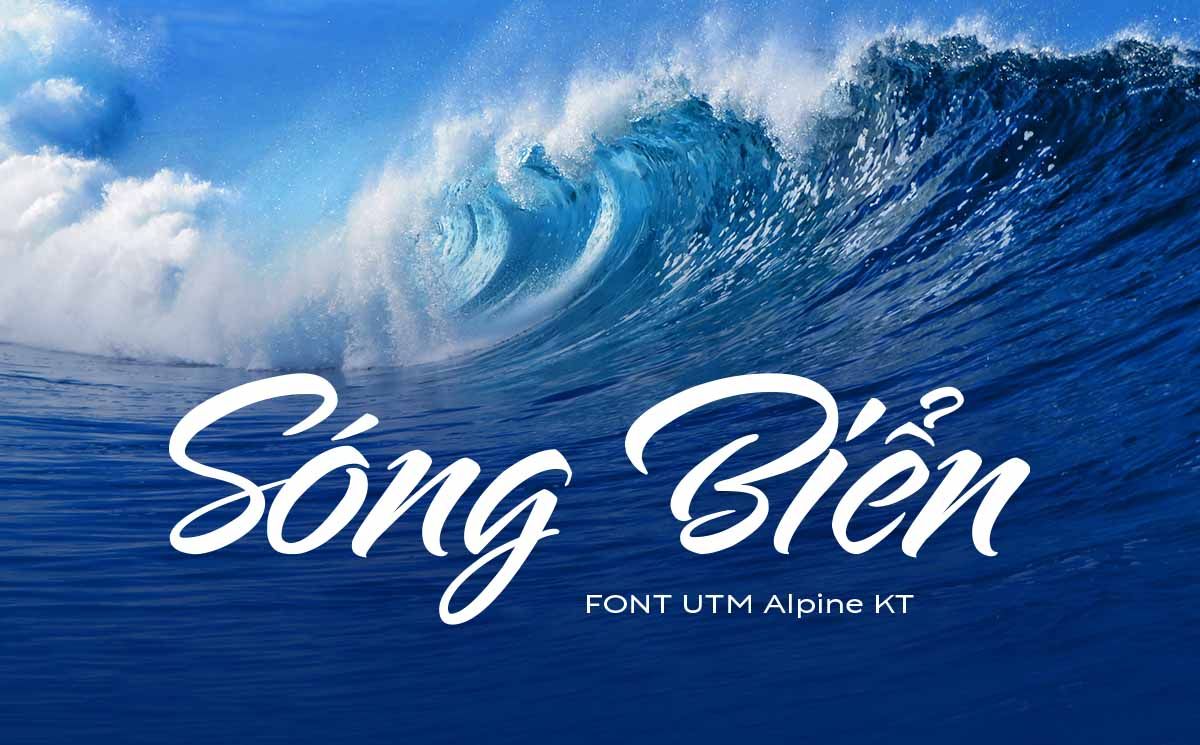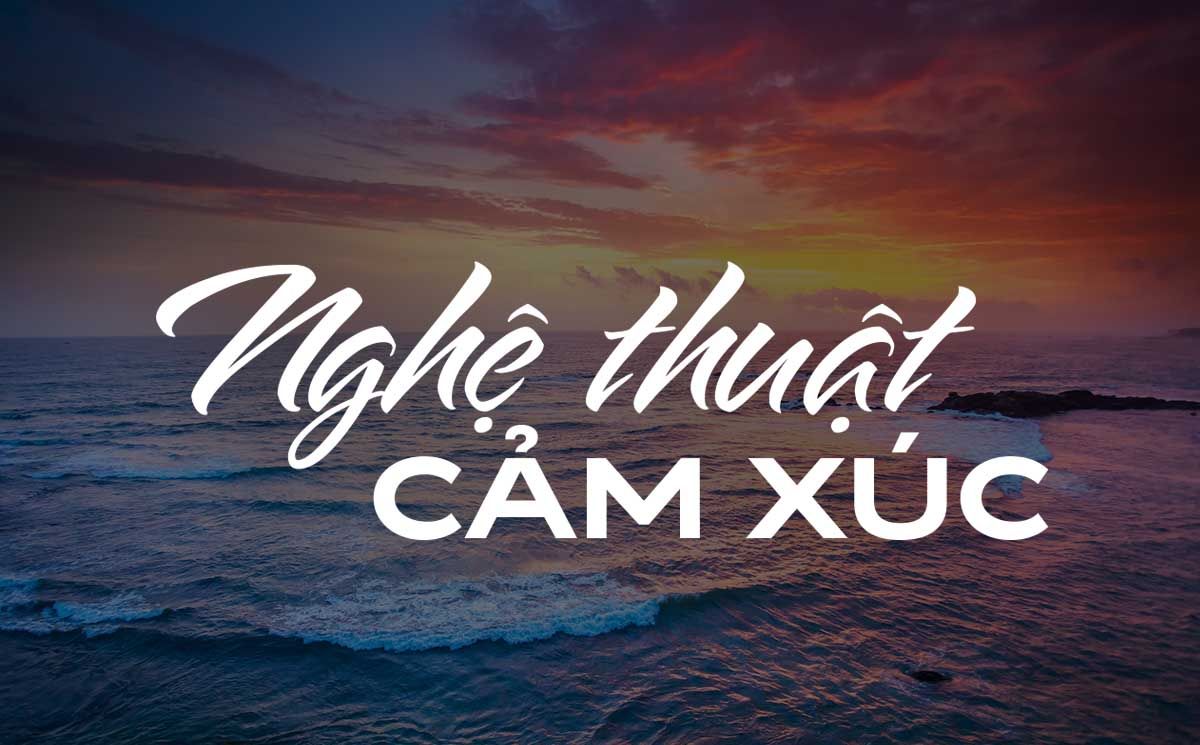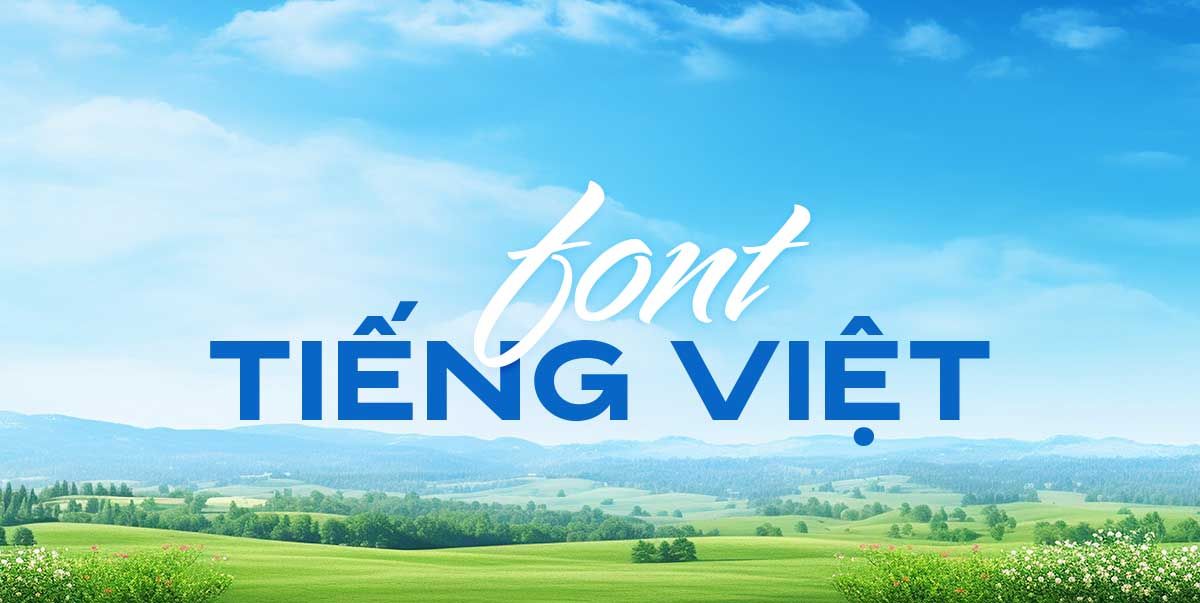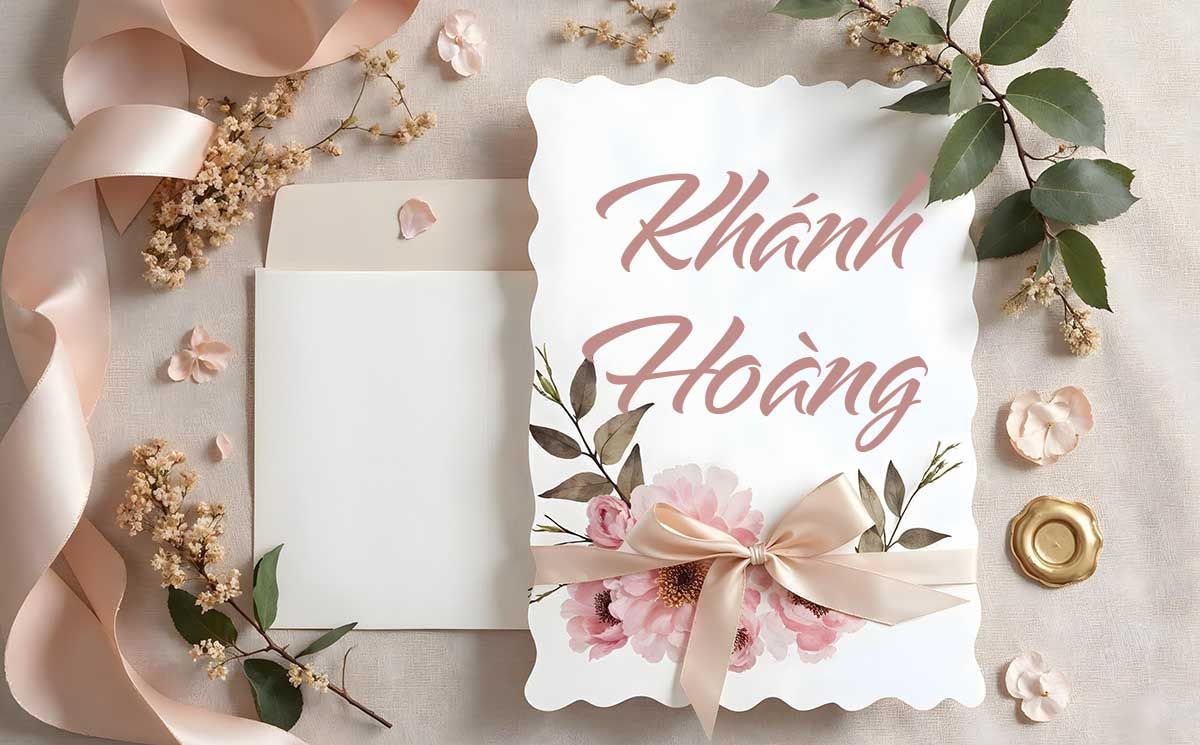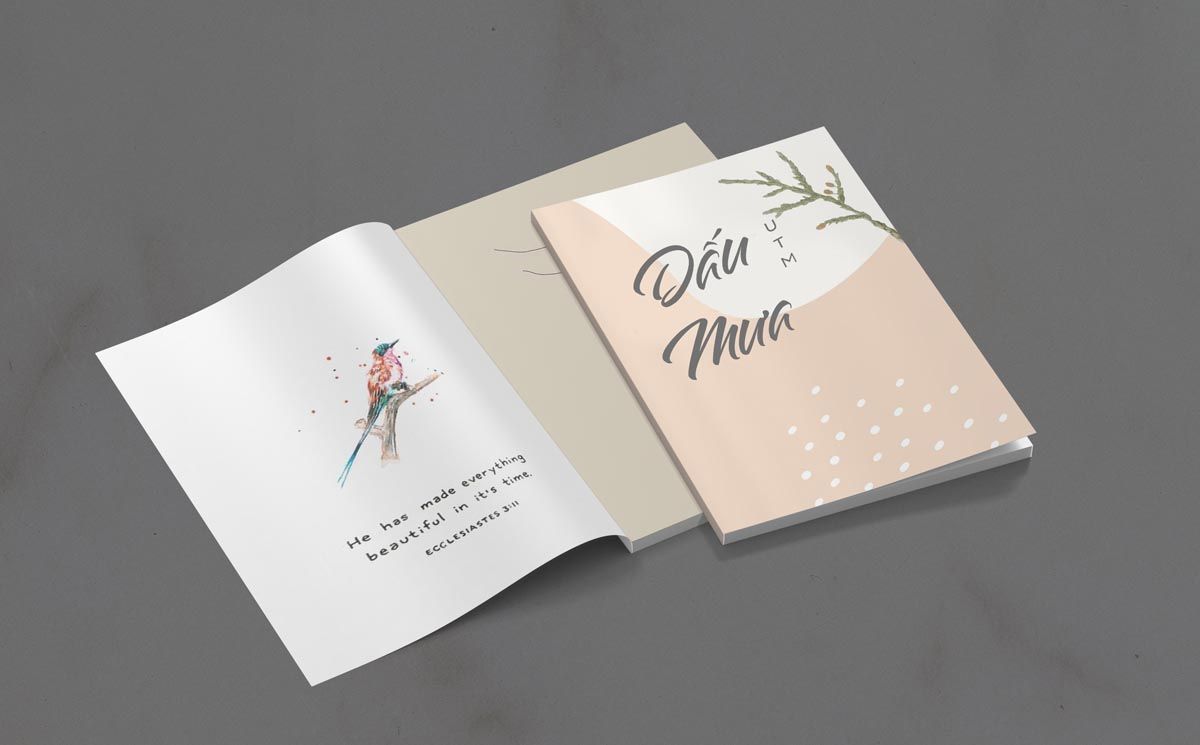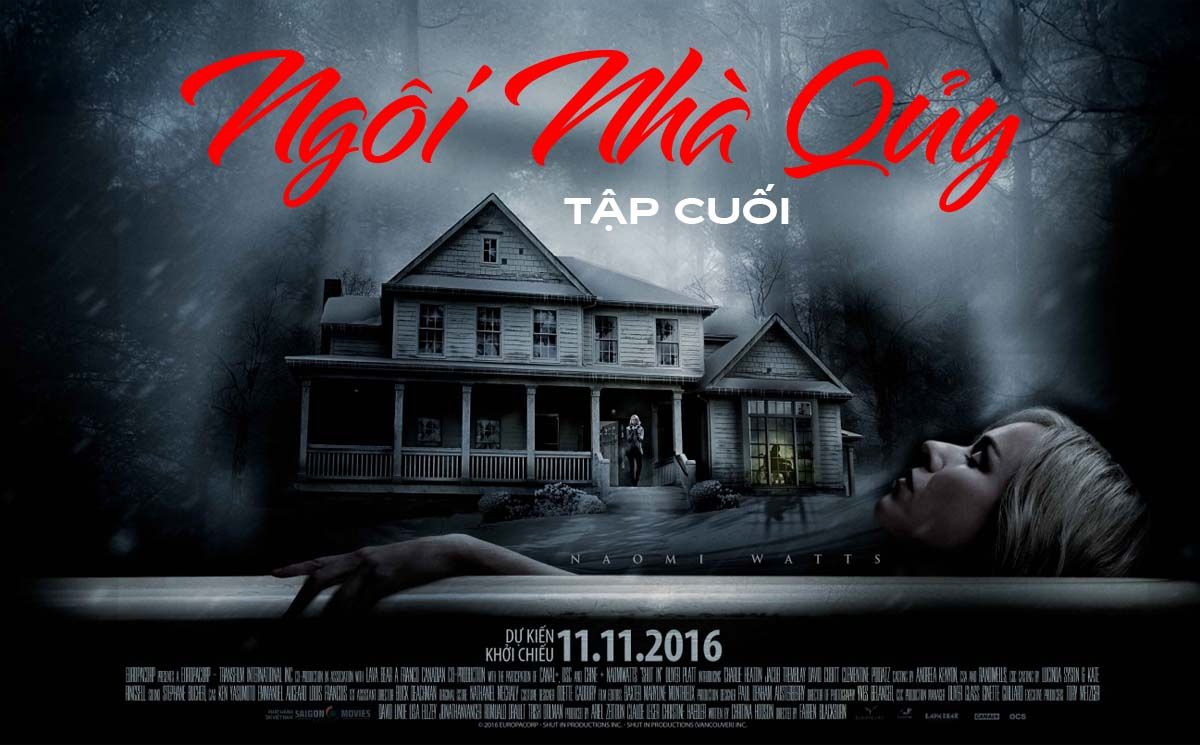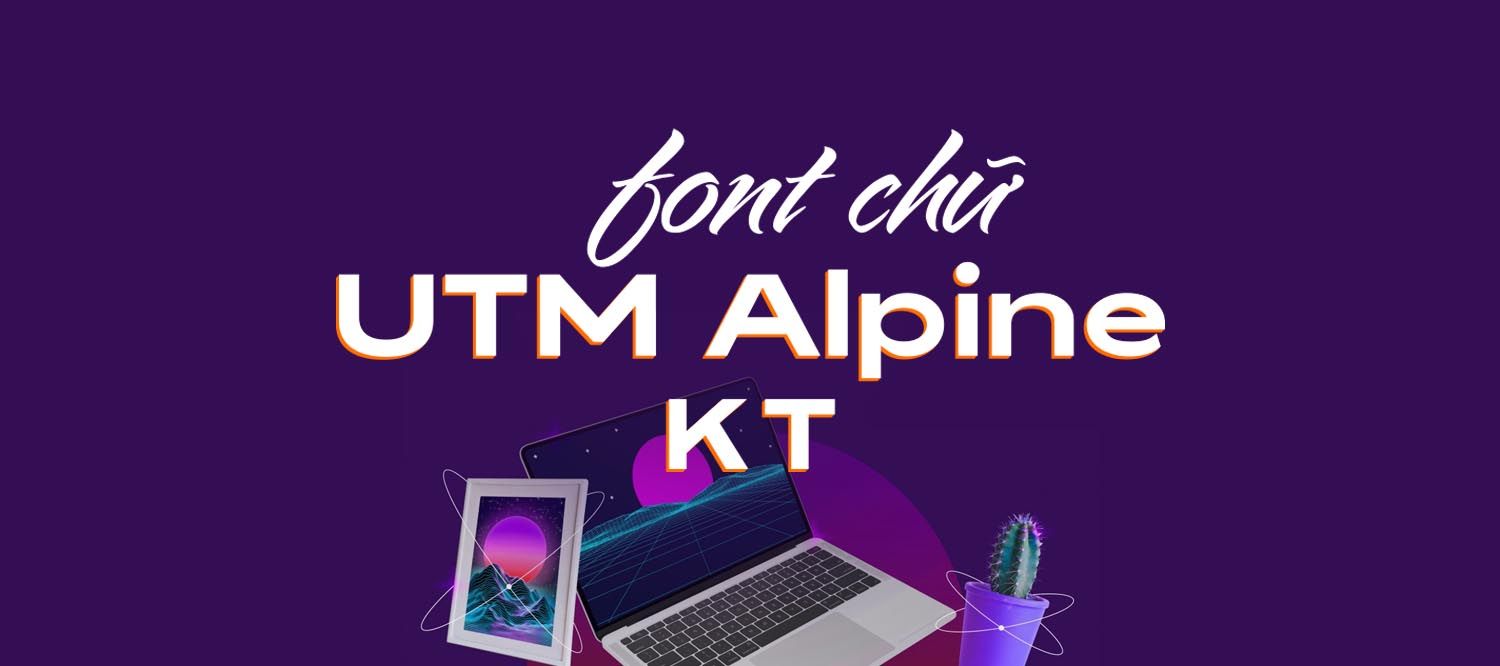
Bạn đang tìm kiếm một font chữ viết tay Việt hóa mang phong cách nghệ thuật, thanh lịch và đầy ngẫu hứng? Font UTM Alpine KT chính là lựa chọn tuyệt vời dành cho các nhà thiết kế đang cần điểm nhấn sáng tạo cho thiết kế tiêu đề, typography hay thiệp mời.
UTM Alpine KT là một font chữ viết tay được Việt hóa bởi nhóm Urban Type Management (UTM) – nổi tiếng với nhiều bộ font đẹp, hỗ trợ đầy đủ tiếng Việt. Phong cách của font mang hơi hướng tự do, phóng khoáng như những nét bút viết tay đầy nghệ thuật.
Font sử dụng các đường nét mảnh, sắc sảo, kết hợp các nét gãy và lượn mềm mại, tạo nên hiệu ứng thị giác đầy ấn tượng. Đặc biệt, các ký tự thường được nối liền, mô phỏng chuyển động mượt mà của bút lông hoặc bút máy.
Font UTM Alpine KT tái hiện lại vẻ đẹp mềm mại của chữ viết tay thủ công, nhưng được cách điệu hiện đại và đầy cá tính. Các nét chữ thanh mảnh, có độ nghiêng nhẹ, giúp tạo nên dòng chảy uyển chuyển, sinh động như đang viết bằng bút máy cao cấp. Những nét đầu – cuối thường được kéo dài một cách tinh tế, mang lại cảm giác tự nhiên, đầy cảm xúc cho từng con chữ.
Một trong những ưu điểm lớn nhất của font UTM Alpine KT chính là khả năng hiển thị tiếng Việt hoàn chỉnh, bao gồm đầy đủ dấu thanh, chữ hoa – chữ thường và các ký tự đặc biệt. Nhờ đó, người dùng hoàn toàn yên tâm khi sử dụng cho các thiết kế mang tính bản địa như: thiệp mời, typography tiếng Việt, tiêu đề báo chí, bìa sách,...
Dù được xếp vào nhóm font chữ viết tay nghệ thuật, UTM Alpine KT vẫn giữ được sự cân bằng giữa thẩm mỹ và tính ứng dụng. Bạn có thể dùng font này cho các dự án cần sự trang nhã, tinh tế (như thiệp mời, thư cảm ơn), hoặc phối hợp với font sans-serif hiện đại để tạo nên các bố cục tương phản sáng tạo trong thiết kế poster, tiêu đề, bao bì...
Với nét chữ mềm mại và thanh lịch, UTM Alpine KT là lựa chọn lý tưởng cho các mẫu thiệp cần sự trang trọng nhưng vẫn gần gũi. Font đặc biệt phù hợp cho thiệp cưới, thiệp sinh nhật, thư mời sự kiện hay các bức thư tay mang đậm tính cá nhân hóa và cảm xúc.
Nhờ sự linh hoạt trong kiểu dáng, font có thể sử dụng làm tiêu đề bìa sách, chuyên đề tạp chí hoặc các ấn phẩm liên quan đến văn hóa, nghệ thuật, lifestyle. Đặc biệt, nó tạo nên vẻ ngoài chỉn chu, thanh lịch mà không quá cứng nhắc – điều mà nhiều font viết tay thường thiếu.
Đối với các thiết kế cần tạo dấu ấn như poster phim ngắn, banner sự kiện nghệ thuật hoặc các chiến dịch truyền thông sáng tạo, UTM Alpine KT giúp tiêu đề trở nên nổi bật hơn, mang theo chất “nghệ” đặc trưng và dễ gây ấn tượng với người xem.
Cuối cùng, font chữ UTM Alpine KT cũng rất phù hợp để in lên bao bì sản phẩm handmade, nhãn mác quà tặng, hoặc các ấn phẩm cá nhân hóa như sổ tay, túi vải, áo thun in chữ... Tính nghệ thuật và gần gũi của font giúp người dùng cảm thấy thiết kế trở nên độc đáo và đầy tâm ý.
Font chữ UTM Alpine KT không chỉ đơn thuần là một font viết tay, mà còn là công cụ truyền tải cảm xúc mạnh mẽ trong thiết kế. Với kiểu dáng mềm mại, phóng khoáng và hỗ trợ đầy đủ tiếng Việt, đây là lựa chọn lý tưởng cho các nhà thiết kế yêu thích sự tự do và tính nghệ thuật.